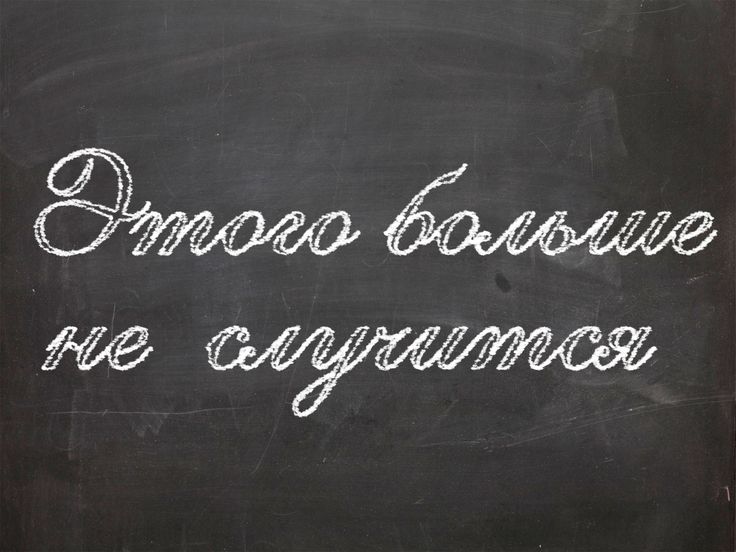
Рукописные шрифты – ключ к индивидуальности
Рукописные шрифты перепрыгнули из школьной тетради в Интернет, и прочно закрепились в среде полиграфии и web-дизайна.
Среди всего многообразия декоративных шрифтов, которые не только дают возможность выгодно подать контент, но так же играют декоративную роль, рукописные шрифты – безусловный лидер. Они отличаются от остальных шрифтов, и выглядят неформальными, интересными и притягательными.
Когда нужно привлечь внимание аудитории, или проект требует индивидуального подхода, используйте рукописный стиль. Правда, при работе с ним нужно учитывать некоторые моменты: использование должно быть уместным, текст хорошо читаемым, и не стоит забывать о том, что рукописный шрифт должен органично вписываться в общий дизайн.
Мы подобрали 20 примеров web-сайтов, в дизайне которых очень удачно и творчески используются рукописные шрифты.
Блог Mariage Gratuit это живой, интересный сайт, с множеством рукописных заголовков и рисованных иллюстраций.
На сайте Javier Guzman красиво используется большой заголовок, который стилизован под надпись мелом с изящными завитками.
Промо-сайт диетической колы также показывает прекрасный пример надписи мелом, которая приправлена легким налетом стиля гранж.
Сайт фильма The Kings of Summer реализует рукописный стиль в логотипе, для того чтобы сделать его более индивидуальным.
Сайт интерактивного дизайнера Andrew Burdin выполнен в классической черно-белой гамме, с размытым изображением гор в качестве фона. Главная страница украшена тонкой цифровой подписью владельца.
Удачное сочетание многослойности, стилизованных иллюстраций и рукописных надписей на свадебном сайте Vince and Marlene, придает ему оригинальный и необычный внешний вид.
BeSmart and Team – сайт с большим количеством графических элементов. Здесь можно найти и градиентные заливки, и круговую навигацию, сложный фон, яркие иллюстрации, и, конечно же, тонкий и искусный рукописный шрифт.
11. ChalkfulЭтот высокий рукописный шрифт от KA Designs полностью воспроизводит аутентичный внешний вид «классной доски». Соедините это с небольшим шрифтом для совершенно симпатичного конечного результата.
12. Шрифт «Возврат отправителю» Романтичный, очаровательный и с любовью винтажный, этот выразительный шрифт от Tom Kolter Fun Shop можно использовать практически в любом проекте — от тем Дикого Запада до сезонные концепции.